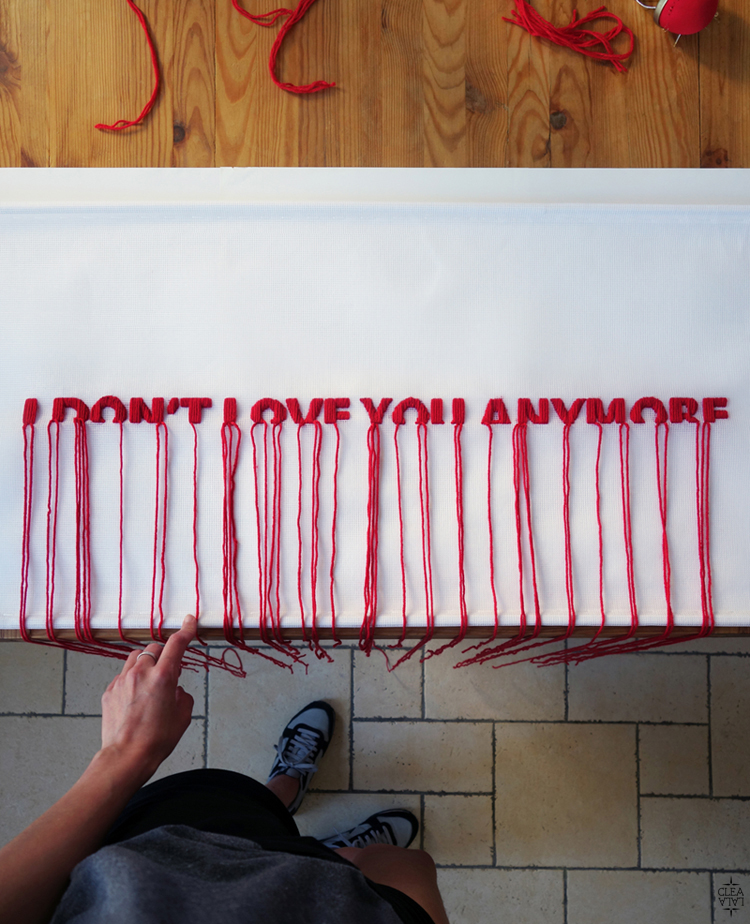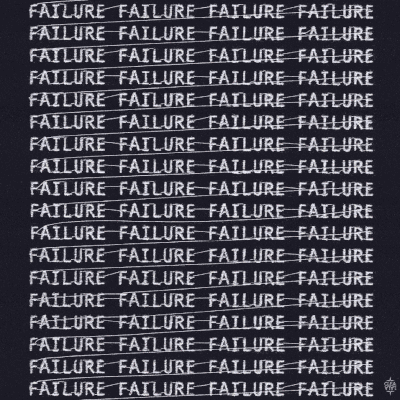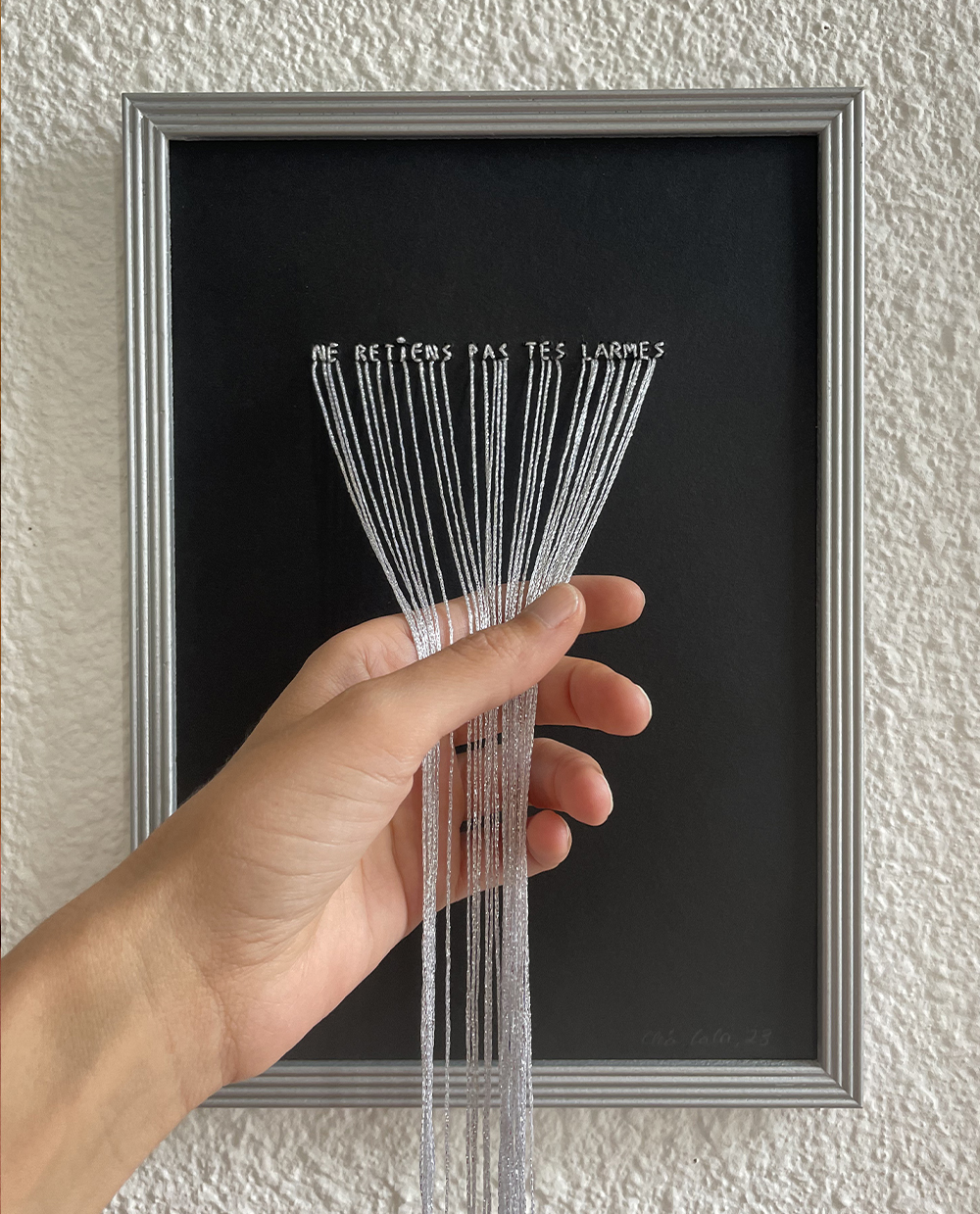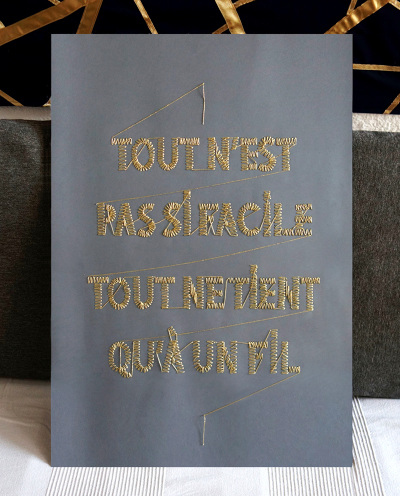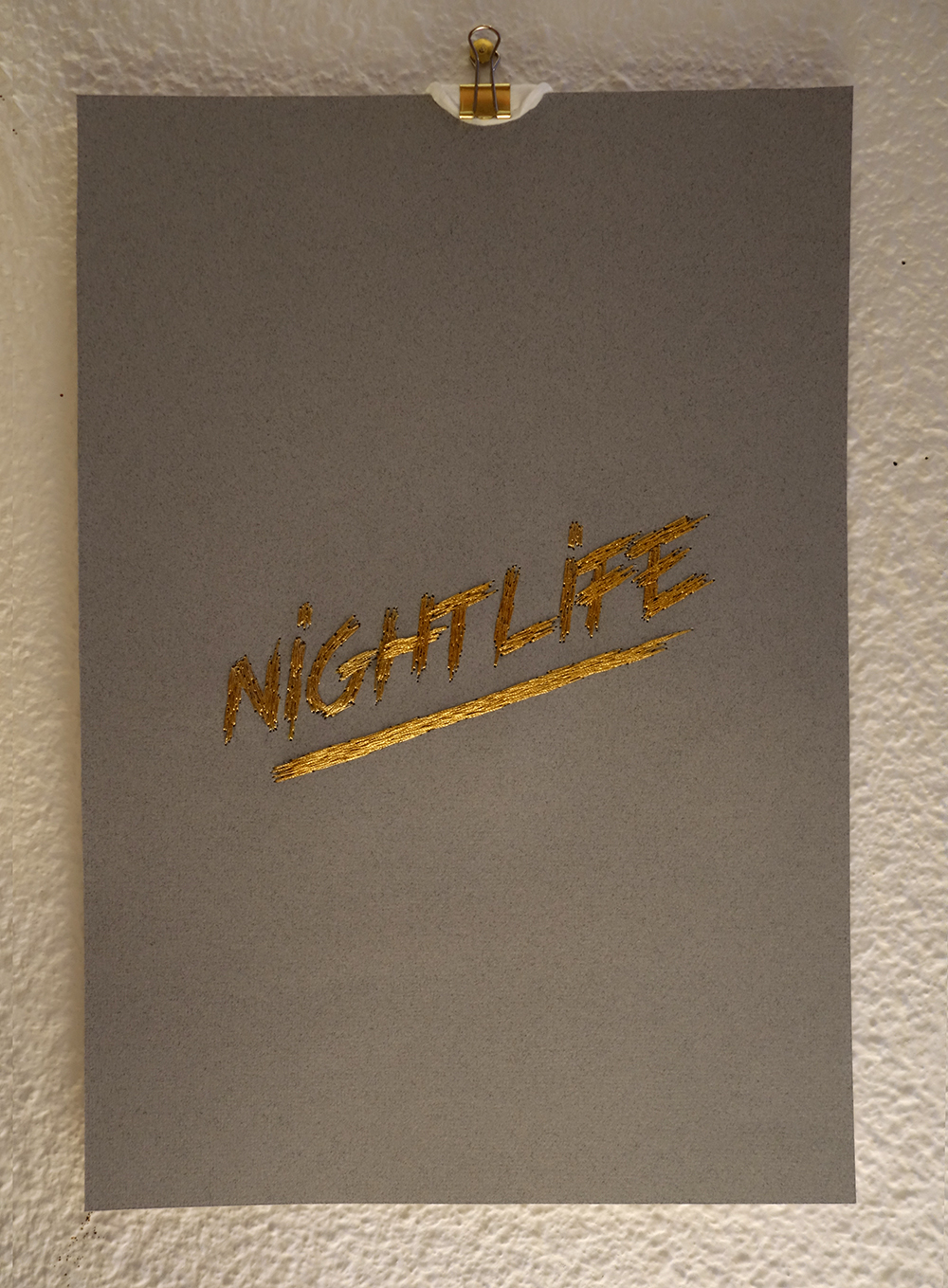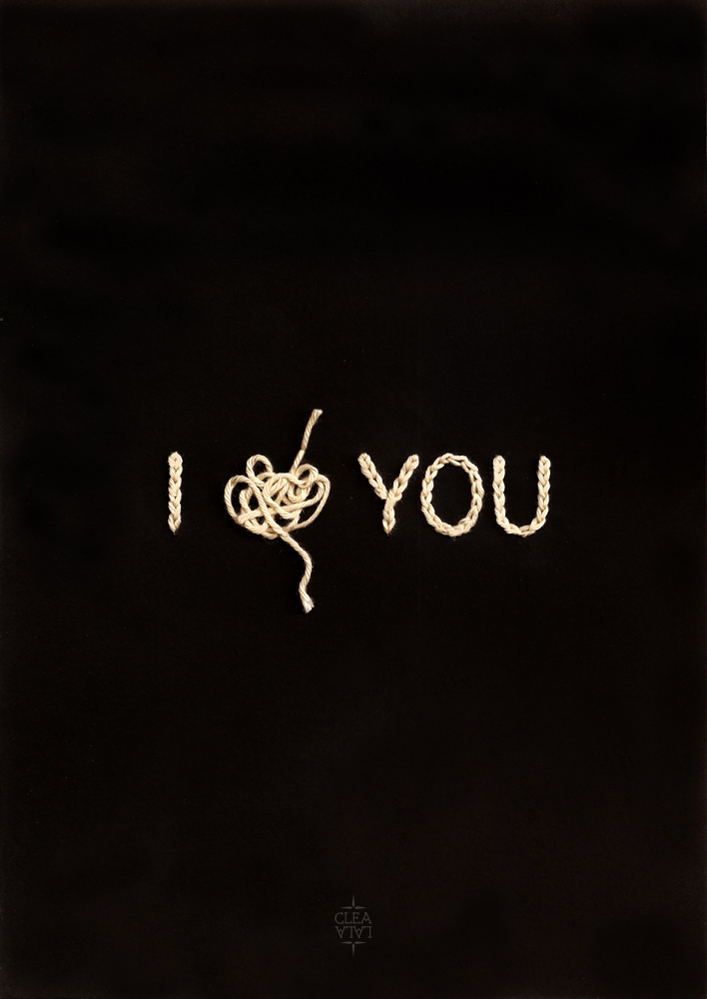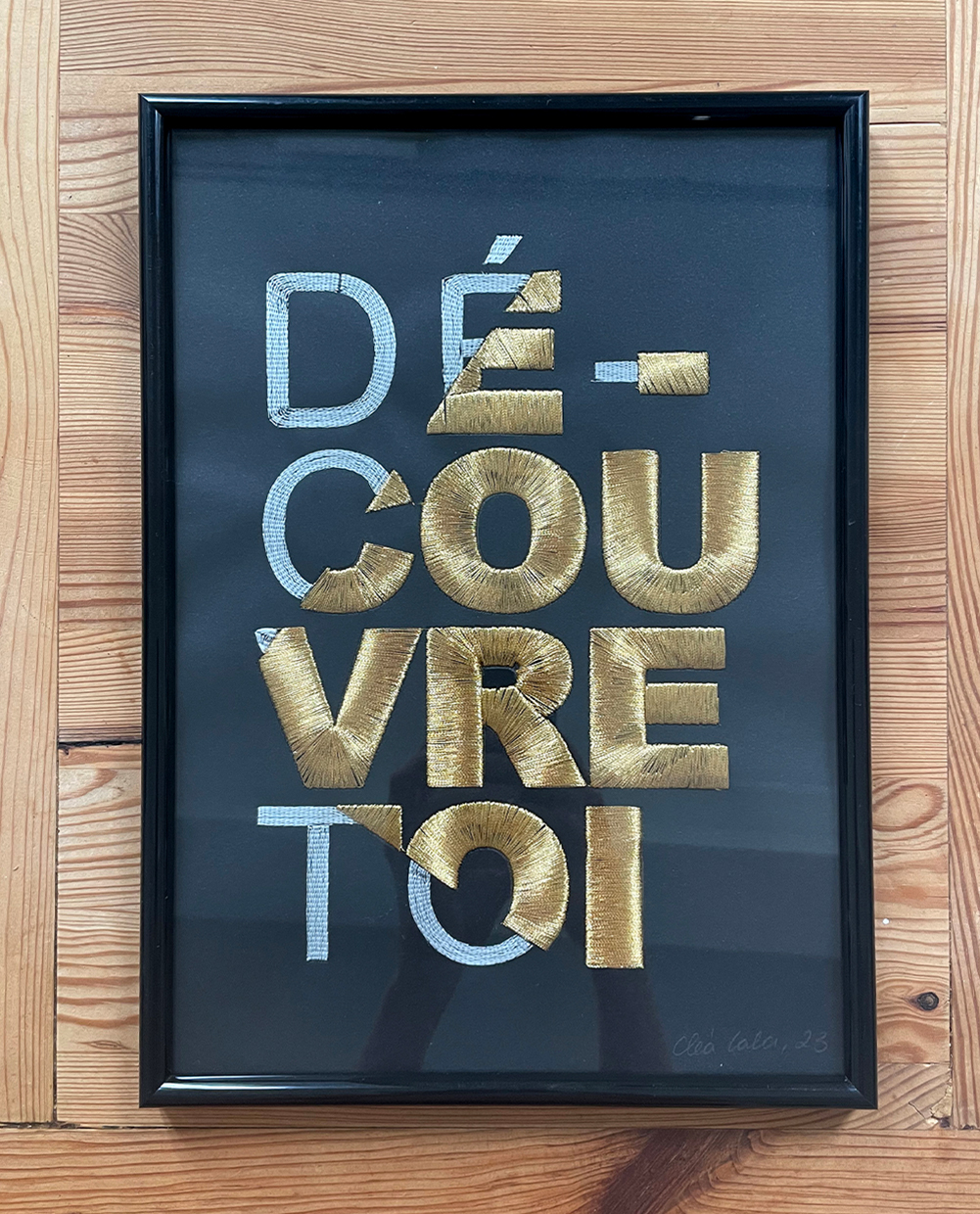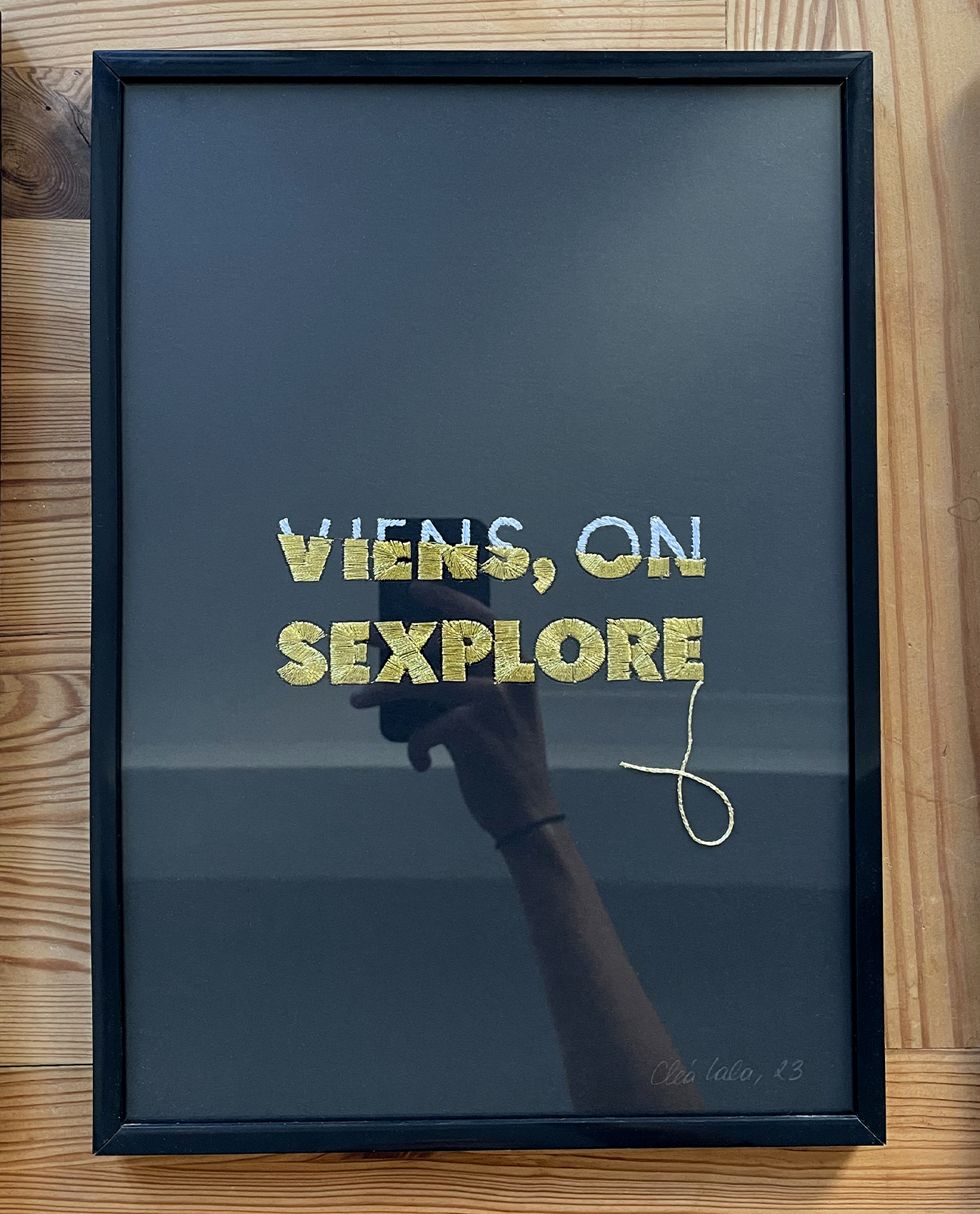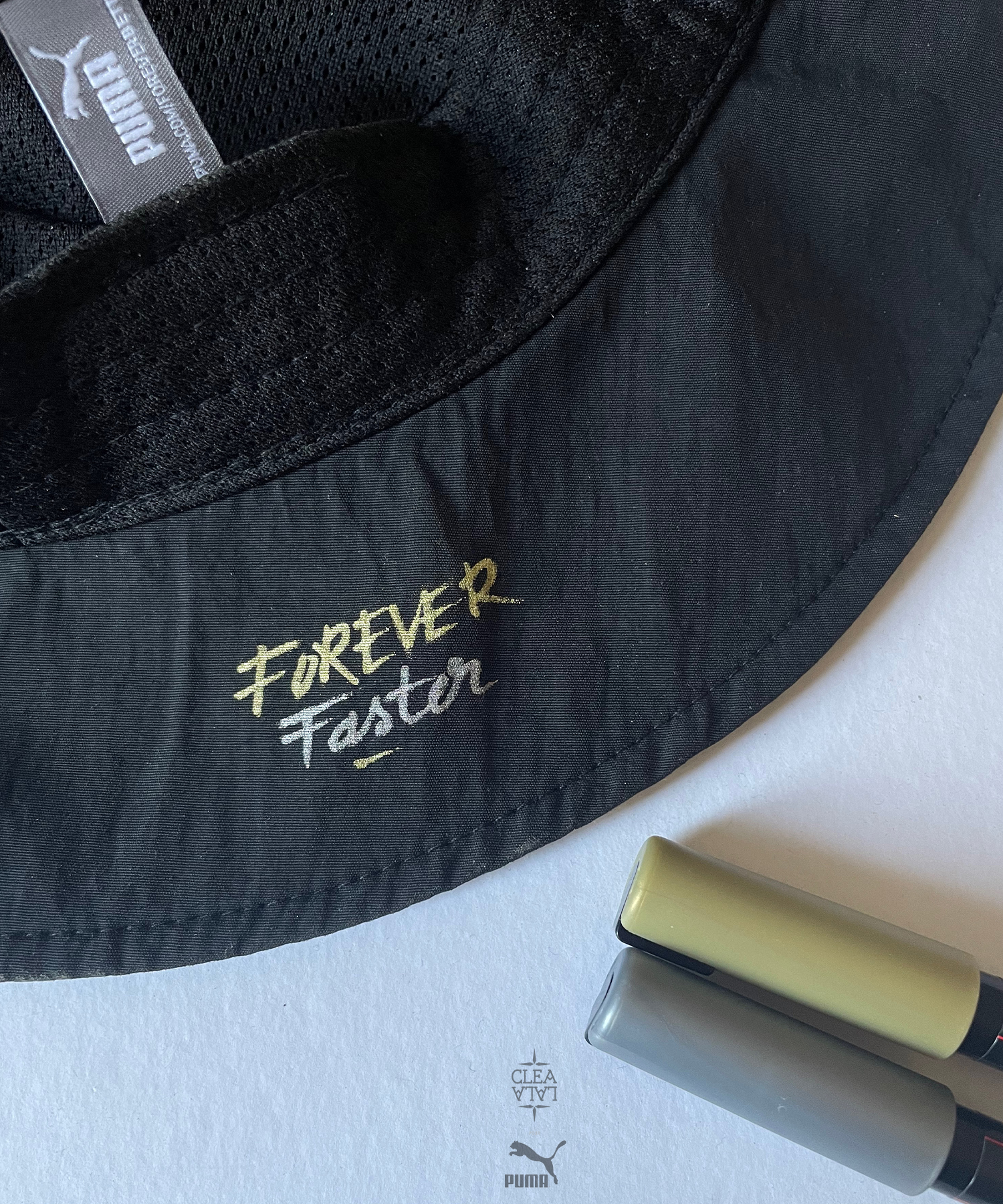
J’aime les lettres et les mots et les phrases : les lignes
J’aime la lettre, les mots et les phrases: les lignes dans tous les sens du terme. Je donne une forme visible à leur sens, au langage et aux émotions. Avec ou sans broderie, en dessinant des lettrages à la main, ou en travaillant des typographies existantes.
Selection de lettrages à l’encre, au fil, ou en digital pour des projets imprimés ou brodés, sur du papier, du textile, des vitrines ou pour le web.
Personnel
Création typographique en fil de laine
CAFÉ SOLO
Création typographique en volume pour habiller la vitrine d’un café
Personnel
Création d’une typographie pour réalisation en un seul fil, sans aucune coupure
ORANGE
FASHION REVOLUTION
Création d’un lettrage code-barre
pour la 4e de couverture du 1er Fanzine du collectif à l’origine de la campagne “Who made my clothes”
NYLON MAGAZINE
Création typographique + animation du logo pour les 12 ans du magazine
ORANGE
Création d’un alphabet motif pour personnaliser son smartphone en boutique
Personnel
Création typograhique digitale + animation d’un texte sur le BUG obsessionnel du désir physique
Création d’un alphabet motif pour personnaliser son smartphone en boutique
Personnel
Création typograhique digitale + animation d’un texte sur le BUG obsessionnel du désir physique
MAISON LUREX
Création de “FLASH-BRODERIES”, Animation
Personnel
Créations personnelles sur le thèmes des cicatrices
LE BON MARCHÉ
Créations typograhiques et composition d’une affiche pour la communication d’une exposition
Personnel
Création de SUMMER VIBES pour céléber l’été, l’eau, la plage
Personnel
Lettrages brodés animés en stopmotion
CAMPAGNES WEB & PRINT
Création de lettrages brodés pour affichages print et web
CLUB PEYROU
Logo signature
pour ROCKSTORE x MYLIFEISAWEEKEND
Personnel
Lettrages digitaux animés
Personnel
Création d’un lettrage lisible en recto/verso
ORANGE
Création digitale de lettrages main pour une collection capsule de coques
PUMA
Création à l’encre de lettrages main personnalisés
Personnel
Lettrages pour différents projets
RESTOS DU CŒUR
Création en fil d’un lettrage + animation pour le vidéo-clip des Restos Du Cœur
LEVI’S
Création de 3 lettrages pour personnaliser sa Trucker au Tailor Shop Champs Élysées
LEVI’S
Création de lettrages main personnalisés
UNDIZ x PAULETTE
Création de 3 lettrages main pour un atelier participatif
Création de lettrages brodés pour affichages print et web
LETTRAGES MAIN
CLUB PEYROU
Logo signature
pour ROCKSTORE x MYLIFEISAWEEKEND
Personnel
Lettrages digitaux animés
Personnel
Création d’un lettrage lisible en recto/verso
ORANGE
Création digitale de lettrages main pour une collection capsule de coques
PUMA
Création à l’encre de lettrages main personnalisés
Personnel
Lettrages pour différents projets
RESTOS DU CŒUR
Création en fil d’un lettrage + animation pour le vidéo-clip des Restos Du Cœur
LEVI’S
Création de 3 lettrages pour personnaliser sa Trucker au Tailor Shop Champs Élysées
LEVI’S
Création de lettrages main personnalisés
UNDIZ x PAULETTE
Création de 3 lettrages main pour un atelier participatif
FLASHBRODERIES
J’ai crée une typographie originale afin de réaliser des mots ou phrases pouvant être brodé.e.s sur différennts supports papiers ou textiles, pour des projets personnels ou des séances de broderies en live lors d’évènements et d’opérations de marques.
DESSINS
J’ai crée un caractère déssiné à la main et décliné en regular + light, pour automatiser la rédaction des titrages de mes dessins et animations .gif